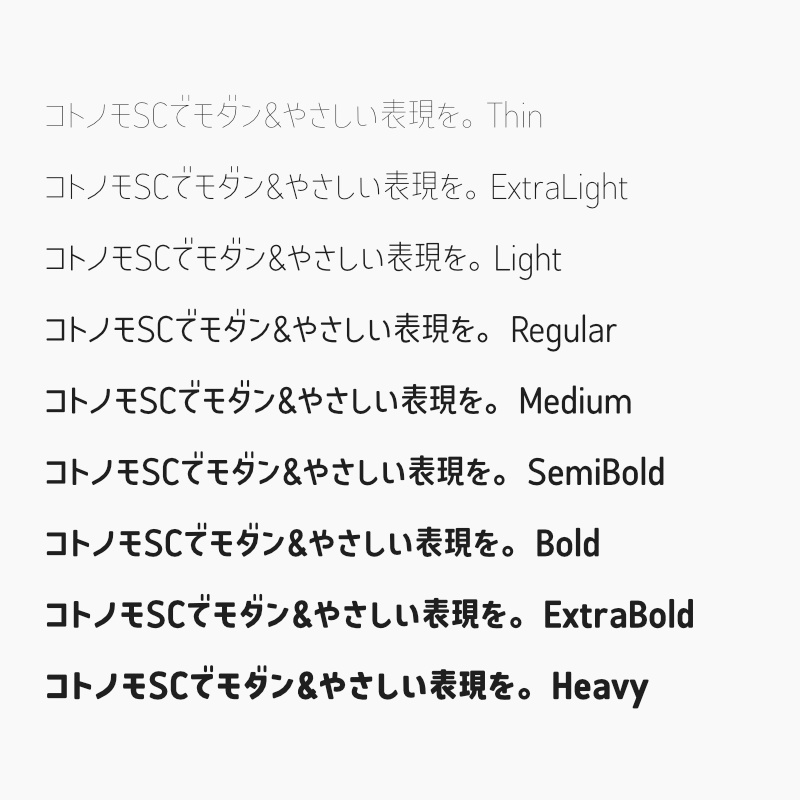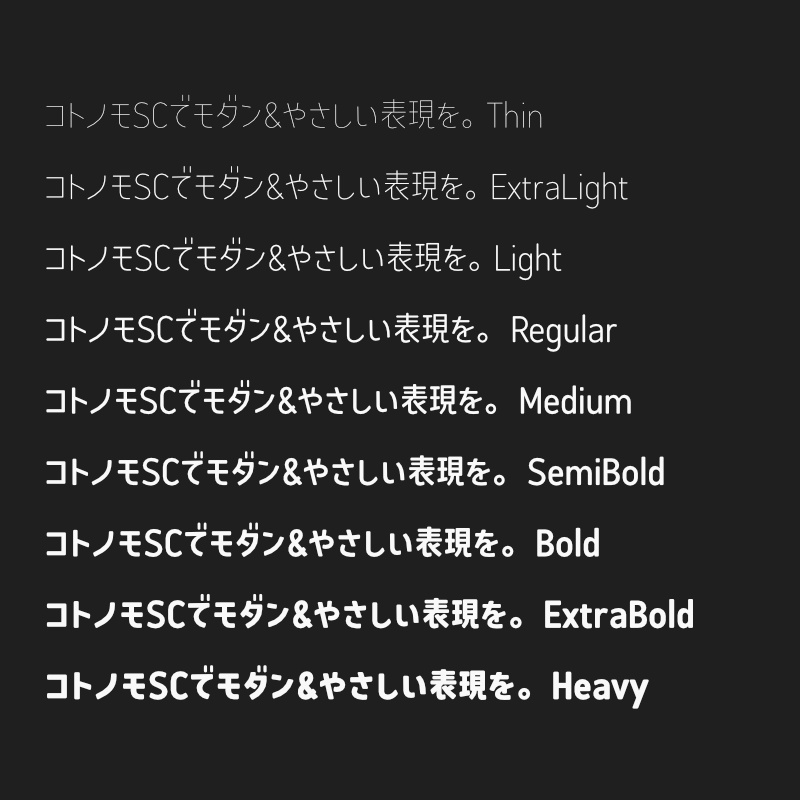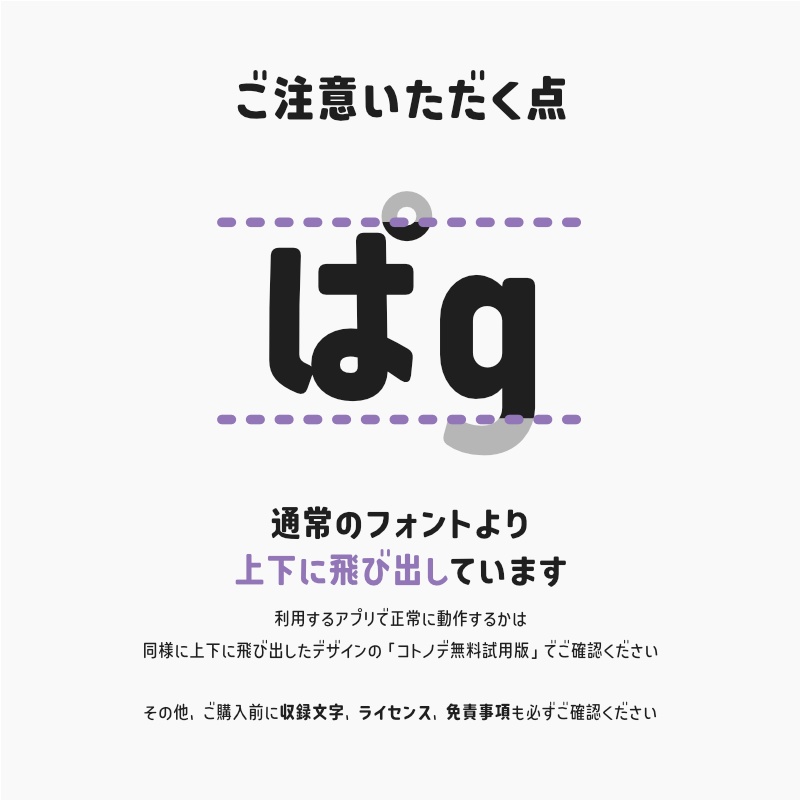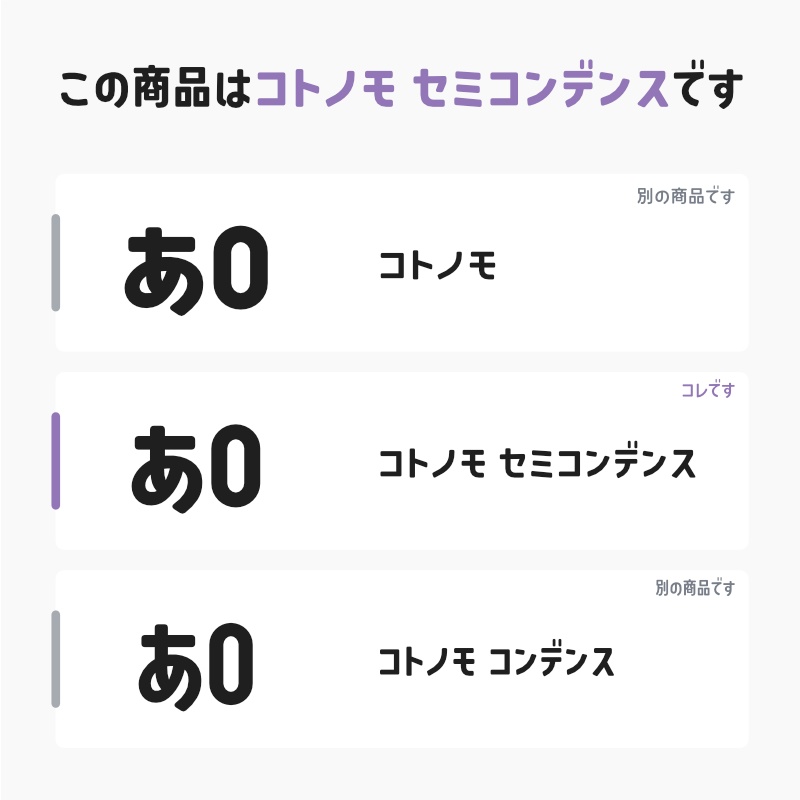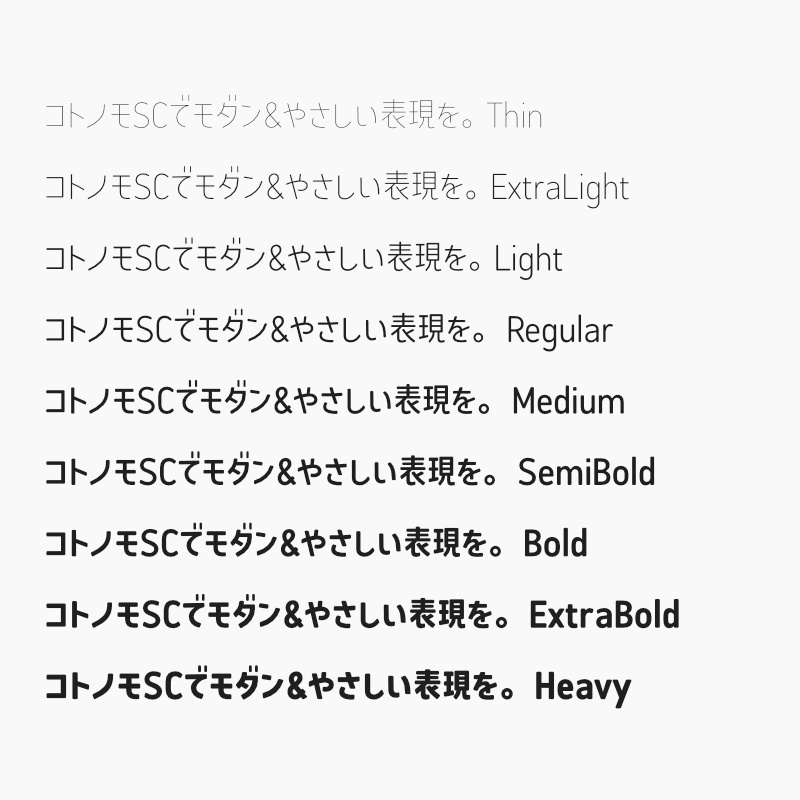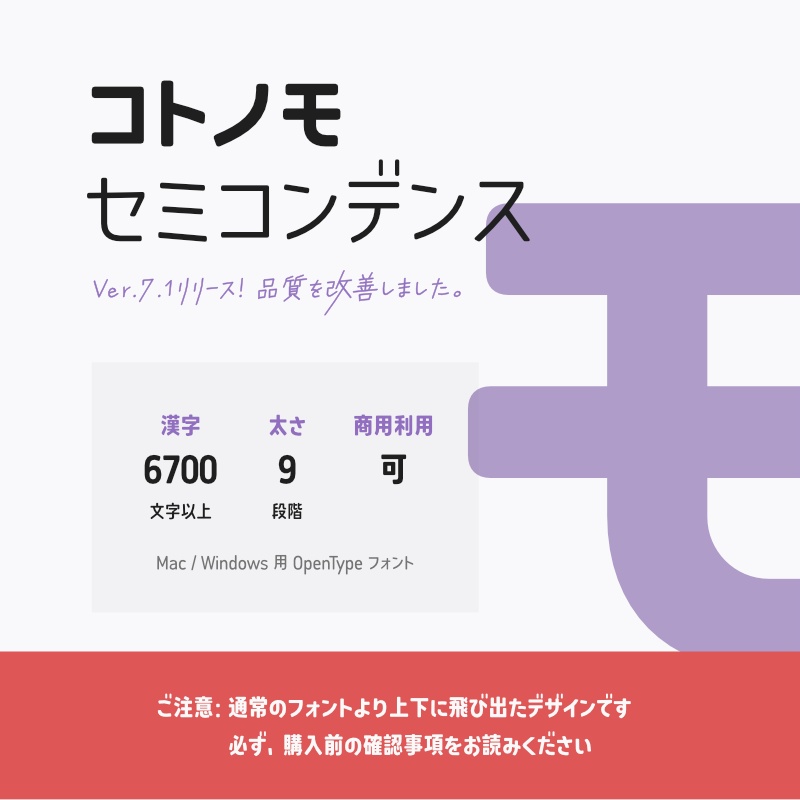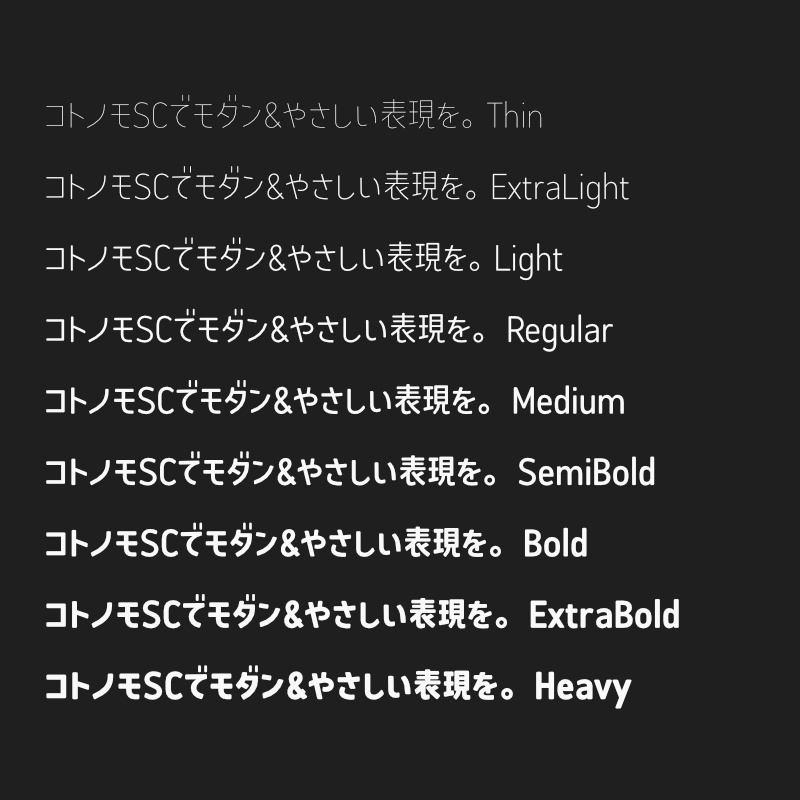
「コトノモ セミコンデンス」フォント(漢字あり) ~少しスリムで角丸でかわいい丸ゴシック体~
・通常のフォントよりも上下にはみ出たデザインです。ご利用のアプリによっては上下が見切れることがあります。ご購入前に確認したい場合は、同様に上下にはみ出たデザインの「コトノデ無料試用版(※)」をご活用ください。 ・漢字は6,700文字以上収録しており、常用漢字・JIS第一水準漢字・JIS第二水準漢字をカバーしています。収録文字は公式の紹介ページをご確認ください。 ・公式の紹介ページの利用規約・免責事項を必ず確認してください(商用利用可・再配布禁止)。 【公式の紹介ページ】 https://kotonohaworks.com/kotonomo-semicondensed.html (※コトノデ無料試用版) https://dkf.booth.pm/items/2727320(無料試用版に漢字は含まれていません。)